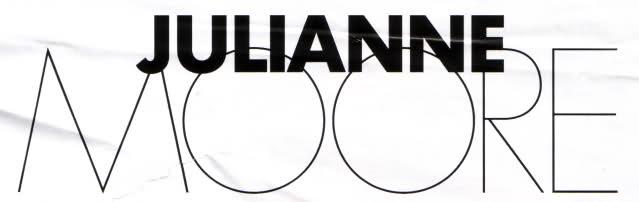
Schrift gesucht
in welcher Schrift ist das wort "MOORE" gesetzt? ich persönlich würde ja Futura sagen, aber der dünnste Schnitt ist noch deutich zu dick - bearbeitete Schrift oder doch eine andere?
Es gibt sehr viele Digitalisierungen der Futura, bei denen auch die Strichstärken sehr untershiedlich ausfallen, das Dein dünnster Schnitt nicht hinkommt, muss noch nichts heißen. Ansonsten bietet dieser Beitrag beim Fontfeed eine gute übersicht üer extraleichte Schriften, hier sind natürlich die geometrischen Serifenlosen interessant.